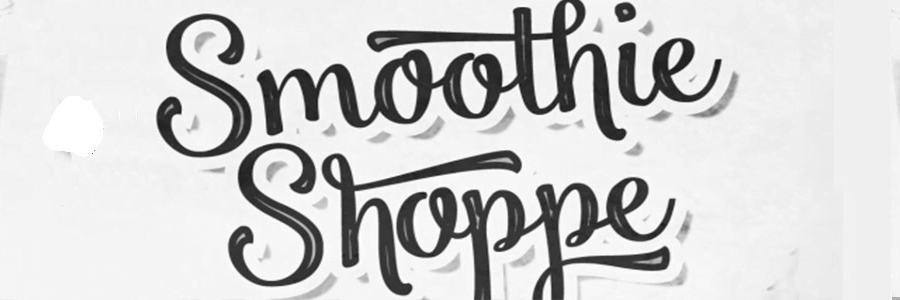
Découvrez la police gratuite d’Emily Spadoni, Smoothie Shoppe. C’est une police super et super flexible qui est disponible en téléchargement gratuit !
Cette typo est livrée avec beaucoup de fonctionnalités, des ponctuations et avec des lettres de connexion vraiment uniques avec des swooshes.
Voici un aperçu en images pour voir ce que vous pouvez réaliser avec cette police et apprécier le projet.